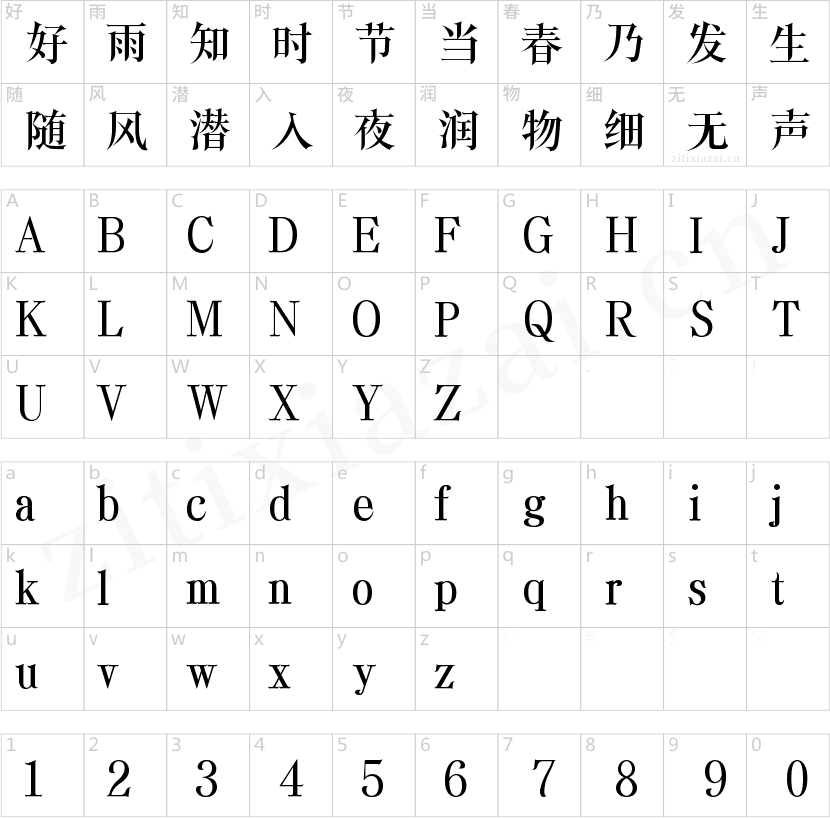
Aa之云体
Aa之云体字体
Aa之云体是一款非常具有艺术性的字体,它的设计灵感来源于对古典艺术的研究,同时又融入了现代字体设计的元素。字形优美,笔画粗细变化自然,给人以大气、典雅的感觉。Aa之云体是一款既传统又现代的字体,它的设计充满艺术感,美观大方,实用性也非常强。无论是对于设计师还是对于普通读者来说,都是一种非常不错的字体选择。Aa之云体适合用于具有艺术感的场合,比如海报、宣传单张、书籍封面等。由于其字形流畅且具有动态感,也适合用于大量的文本排版,如报纸、杂志等。